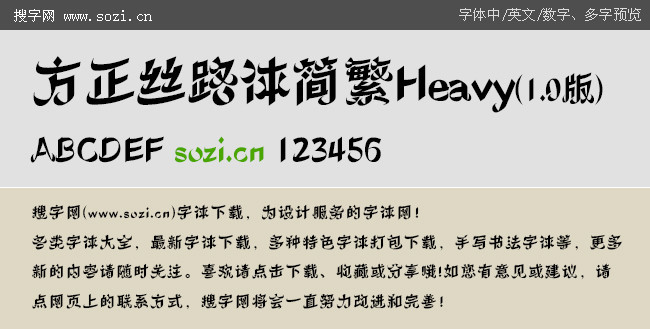
方正丝路体简繁Heavy1.0
搜字网提供一款方正丝路体简繁Heavy1.0中文字体下载,方正丝路体在笔画方面,有着自己特有的造型特征,撇和捺的折笔处、收尾处,需要灵活掌握幅度、大小,这些都会影响整个字的气质与态势;还有竖笔、撇笔,在笔画横竖交叉的地方做了气口的处理,能够适用于艺术设计、包装印刷、签名设计、图形设计等应用。(本字体为个人非商用版,如需要商用请联系方正公司购买版权)